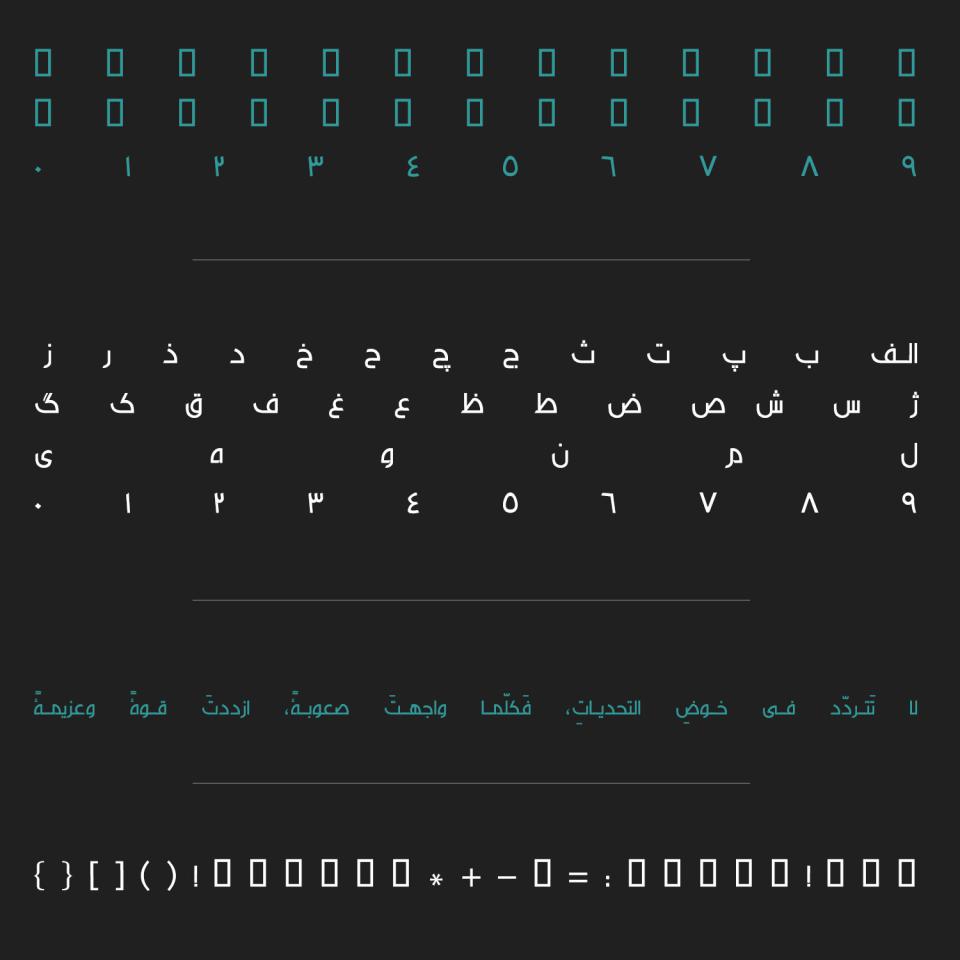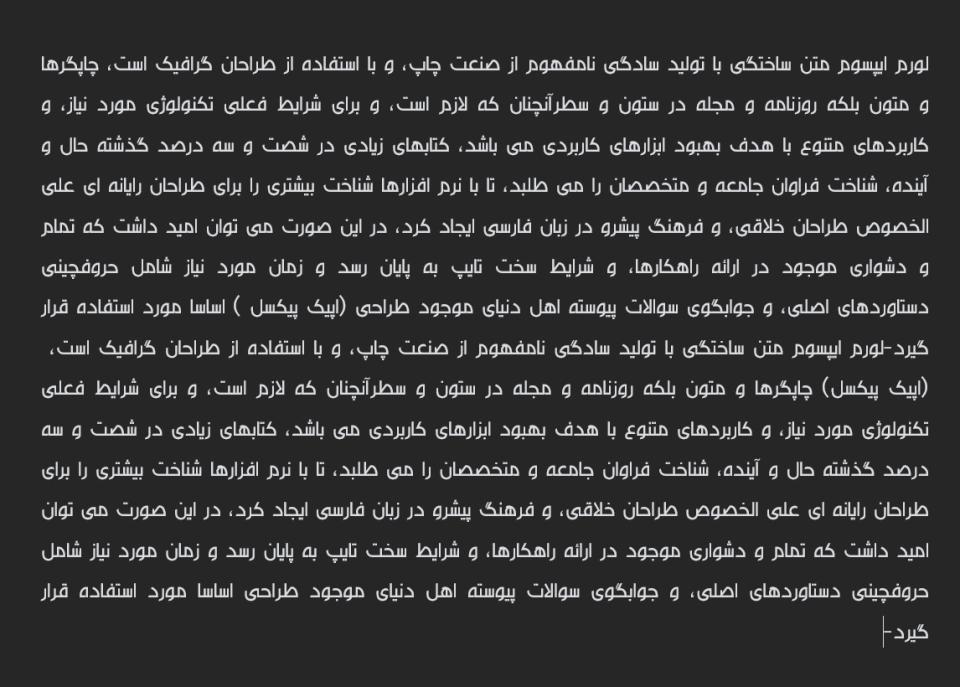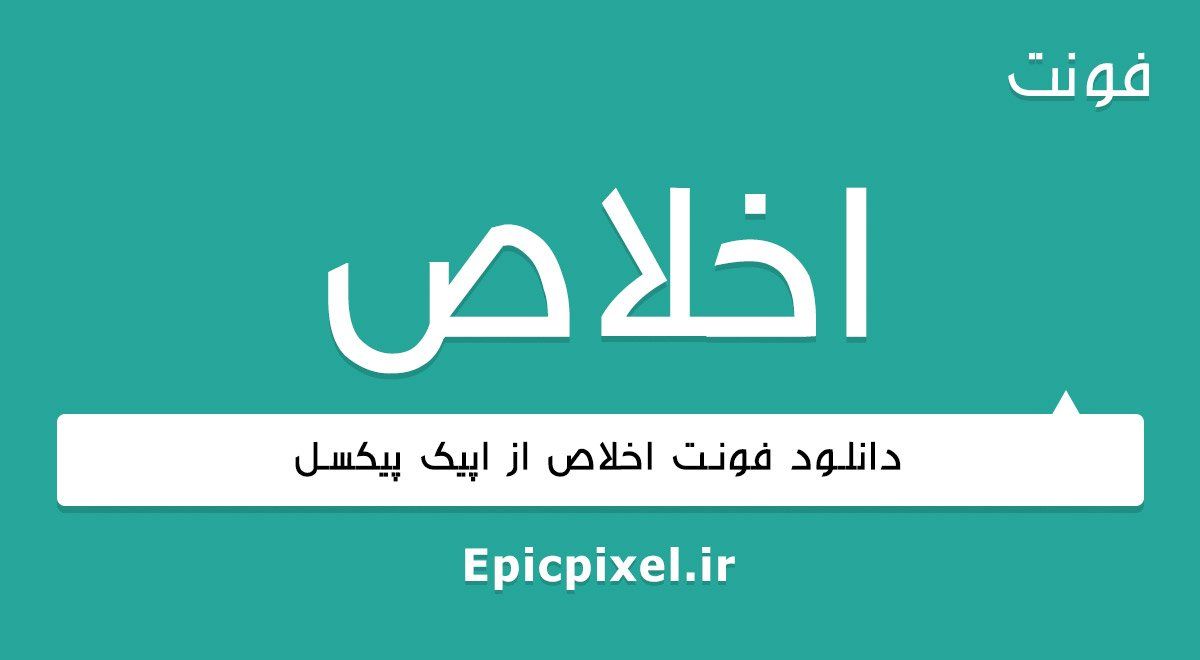
3 فونت اخلاص فارسی Ekhlass
فونت اخلاص فارسی، با طراحی منحصر به فرد خود، گزینه ای ایده آل برای کسانی است که به دنبال تایپوگرافی خاص و چشم نواز هستند. این فونت، با ساختار هندسی دقیق و خطوط نرم، تعادلی ظریف بین مدرنیته و اصالت ایجاد می کند. اگر به دنبال فونتی هستید که در عین خوانایی بالا، جلوه ای متفاوت به نوشته های شما ببخشد، اخلاص انتخاب مناسبی است.
یکی از ویژگی های برجسته این فونت، تنوع در وزن ها و استایل هاست که به شما اجازه می دهد در طراحی های مختلف، از عناوین گرفته تا متن های طولانی، از آن بهره ببرید. این تنوع، دست شما را در خلق آثار خلاقانه باز می گذارد. در طراحی لوگو، پوستر، جلد کتاب یا حتی وب سایت، فونت اخلاص می تواند به عنوان عنصری کلیدی، هویت بصری منحصربه فردی را به کار شما ببخشد.
با وجود ظاهر مدرن، اخلاص ریشه هایی در خوشنویسی سنتی فارسی دارد و این تلفیق، حسی نوستالژیک و در عین حال امروزی را القا می کند. این ویژگی، آن را برای استفاده در پروژه هایی که به دنبال ایجاد ارتباط بین گذشته و حال هستند، بسیار مناسب می سازد. البته باید در نظر داشت که به دلیل طراحی خاص، شاید این فونت برای متن های بسیار طولانی با سایز کوچک، کمی خسته کننده باشد. اما در مجموع، فونت اخلاص با ارائه ترکیبی جذاب از زیبایی و کارایی، انتخابی هوشمندانه برای طراحان و علاقه مندان به تایپوگرافی فارسی است و از همه مهمتر، رایگان بودن آن، فرصتی استثنایی برای بهره مندی از این فونت ارزشمند را فراهم می کند.